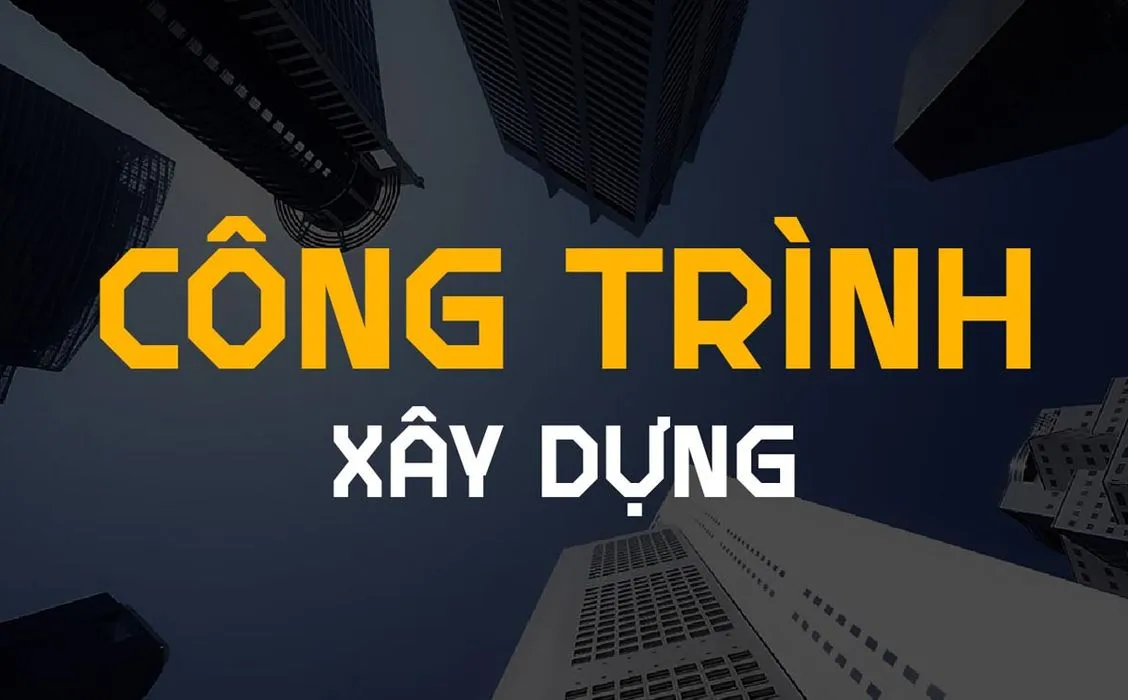
Font chữ cứng cáp cho lĩnh vực xây dựng TH ANSERS Việt Hoá
Font chữ TH ANSERS - Sự Kết Hợp Hoàn Hảo Giữa Sự Cứng Cáp và Năng Động Cho Thiết Kế Poster, banner và logo
Trong thế giới thiết kế đồ họa, font chữ không chỉ đơn thuần là một công cụ ghi chép mà còn là một yếu tố quan trọng để truyền đạt thông điệp, tạo nên sự hấp dẫn và thể hiện phong cách độc đáo. Và nếu bạn đang tìm kiếm một loại font chữ in hoa mang tính cứng cáp và năng động để tạo nên những bức tranh thị giác ấn tượng, thì TH ANSERS chính là sự lựa chọn hoàn hảo.
TH ANSERS là một font chữ độc đáo, nổi bật với những đường nét mạnh mẽ và sắc sảo. Được thiết kế với tinh thần hiện đại và sáng tạo, các chữ cái in hoa trong bộ font này tỏ ra cứng cáp và linh hoạt đồng thời. Khả năng kết hợp giữa sự cứng cáp và năng động giúp nó không chỉ phù hợp cho các dự án thiết kế liên quan đến thể thao, cuộc sống đô thị mà còn cho các ấn phẩm poster sự kiện và thậm chí cả các dự án đòi hỏi tính nghệ thuật cao.
Với việc áp dụng font chữ TH ANSERS, bạn có thể tạo ra những tác phẩm đầy sức mạnh và sự lôi cuốn. Từ những tựa đề mang tính chiến đấu đến những thông điệp động viên, tác giả biết cách tạo ra sự tương tác độc đáo và đem lại một trải nghiệm thị giác đặc biệt cho người xem.
Không chỉ dừng lại ở vẻ cứng cáp, TH ANSERS còn thể hiện sự năng động và trẻ trung qua từng đường nét khúc triết mạnh mẽ. Điều này tạo nên một sự cân đối hoàn hảo giữa tính thể thao và sự tươi mới, thể hiện rõ ràng trong các chi tiết của các chữ cái và ký tự đặc biệt. Điều này khiến cho TH ANSERS trở thành lựa chọn tối ưu cho những dự án thể hiện sự độc đáo và phong cách.
Tóm lại, font chữ TH ANSERS không chỉ là một bộ phông chữ đơn thuần, mà là một công cụ sáng tạo mạnh mẽ để bạn thể hiện phong cách độc đáo trong việc thiết kế poster và các tác phẩm thị giác khác. Với sự kết hợp hoàn hảo giữa cứng cáp và năng động, TH ANSERS là nguồn cảm hứng không thể bỏ lỡ cho những ai đam mê sự đột phá và sáng tạo trong lĩnh vực thiết kế đồ họa.